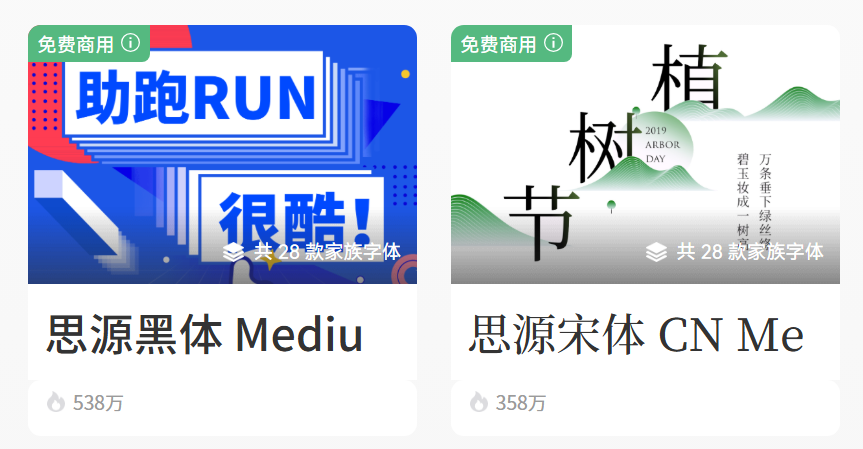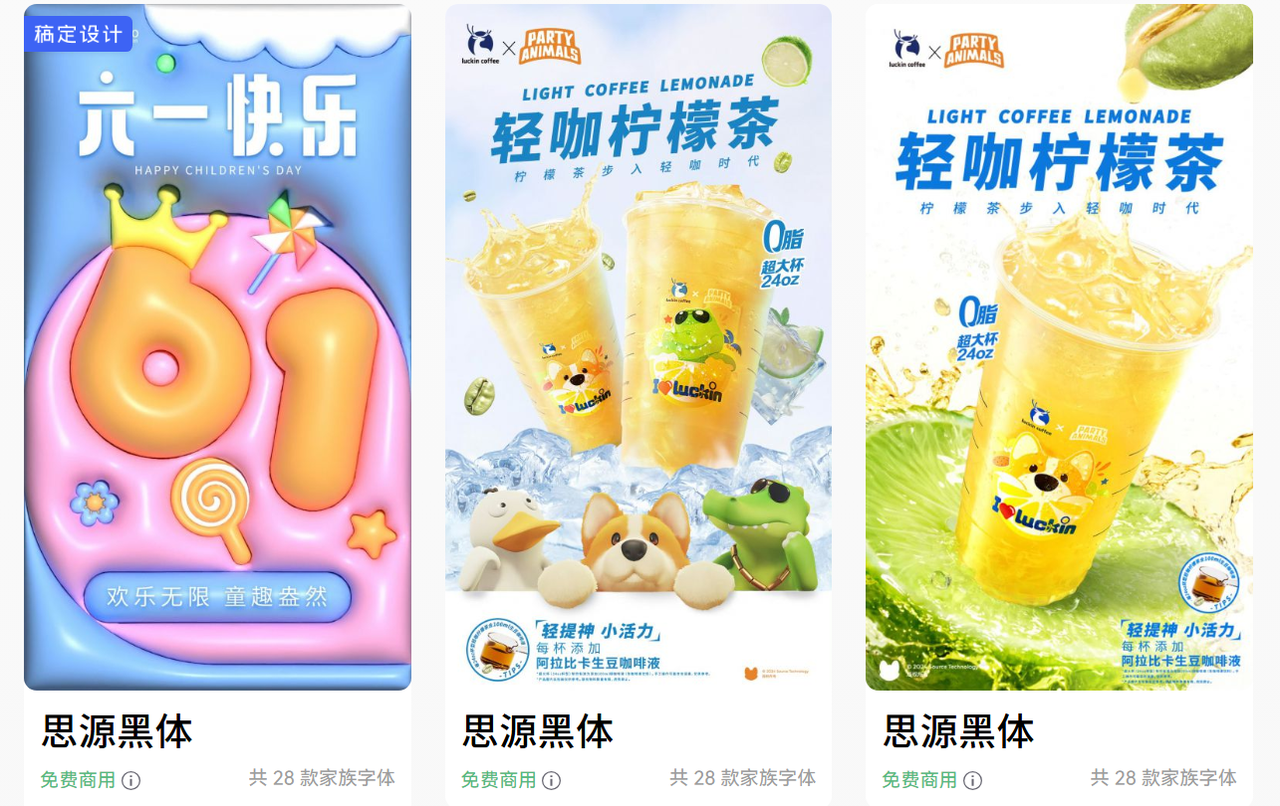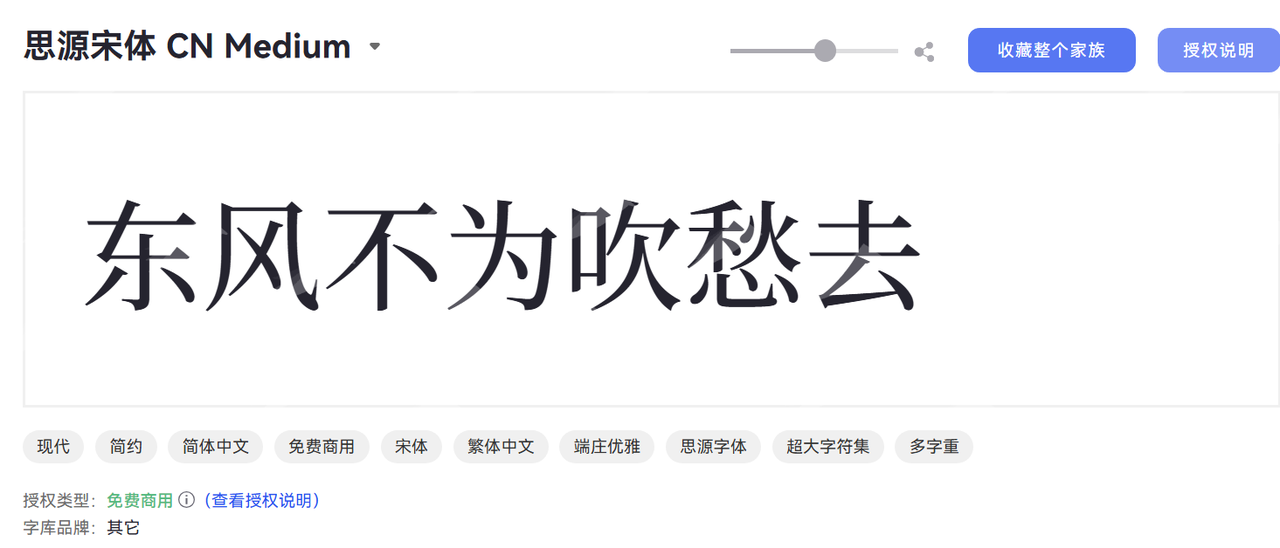
做设计的人,最怕两件事:找不到好字体,和用了不该用的字体。思源字体由 Adobe 与 Google 联合开发,你可以免费下载、免费商用、免费修改,用在海报、电商主图、短视频封面、App 界面,乃至印刷品,统统没有后顾之忧。2026 年,思源字体家族持续扩充,字重覆盖更广,语言支持更完善。本文以字由网为例,带你盘点当前可用的全部思源免费商用字体,并手把手讲清楚下载与使用方式。
1.思源黑体
思源黑体整个思源系列里使用频率最高的一款。字形现代、笔画干净、视觉重心稳,适合 UI 界面、电商主图、PPT、正文排版等几乎所有需要「说清楚」的场景。7 个字重从极细到极粗一应俱全,设计弹性极大。
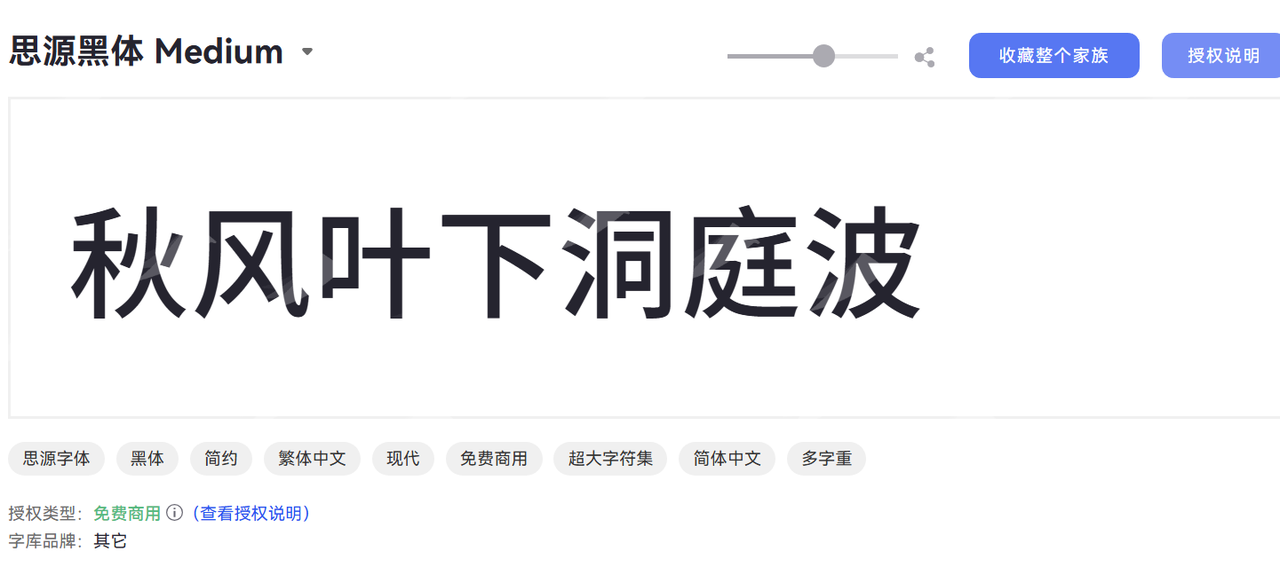
2.思源宋体
有人说思源宋体是目前免费字体里气质最好的一款,这话并不夸张。它的笔锋处理细腻,横竖对比分明,兼顾印刷感和屏显清晰度,特别适合书籍排版、高端海报、品牌物料、节气类新媒体封面,凡是需要「有腔调」的地方,首选它。
目前,很多电影海报和品牌广告都会使用思源宋体做宣传,思源宋体能够满足精细化排版需求,而且在阅读场景中舒适度远超普通宋体。